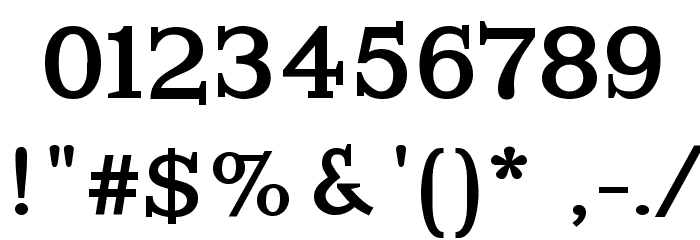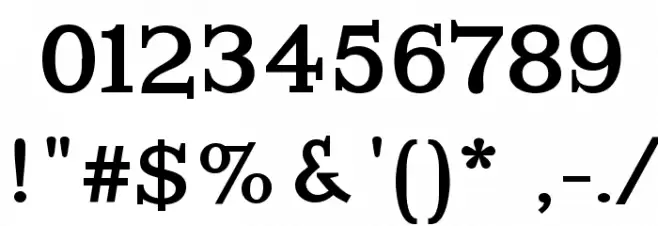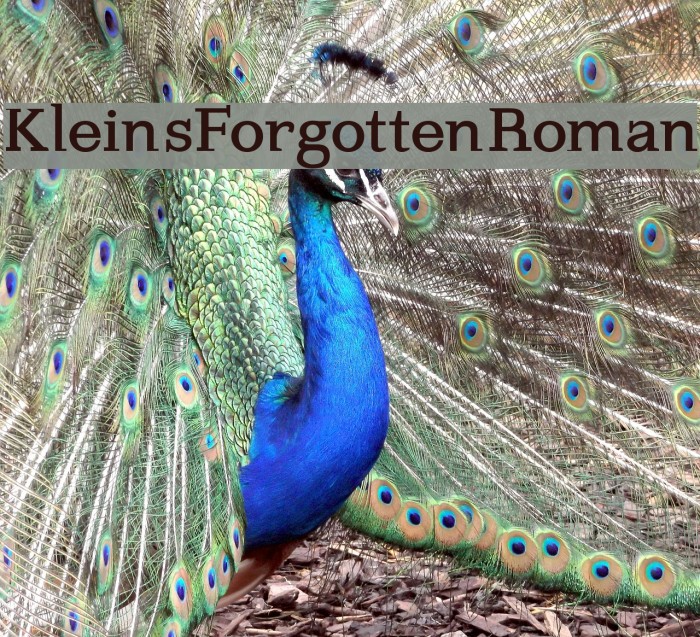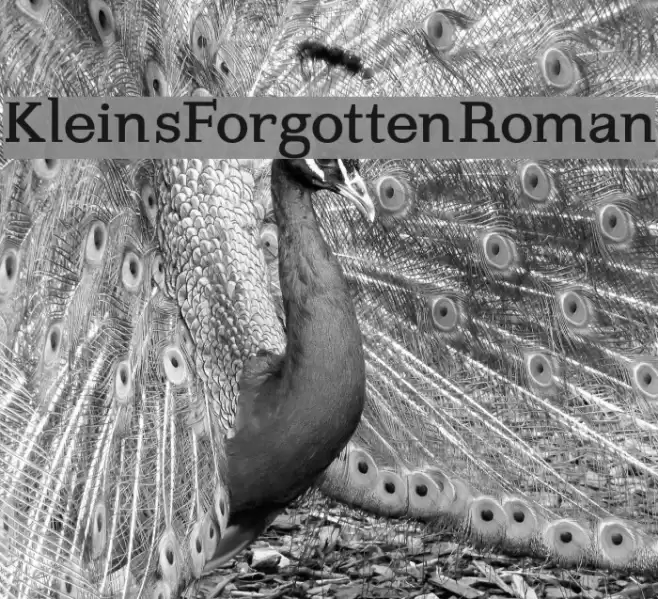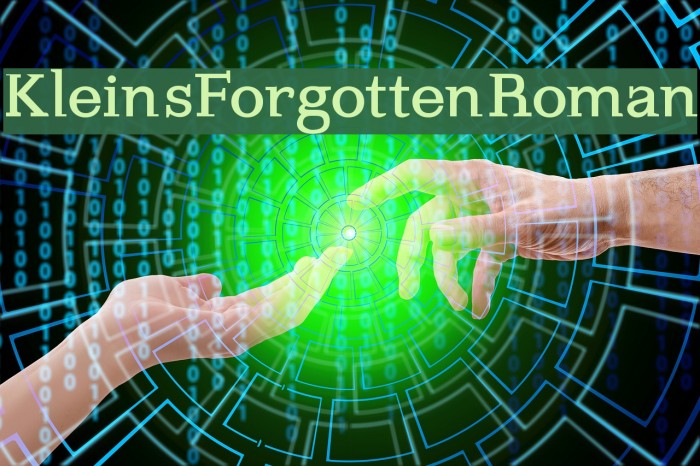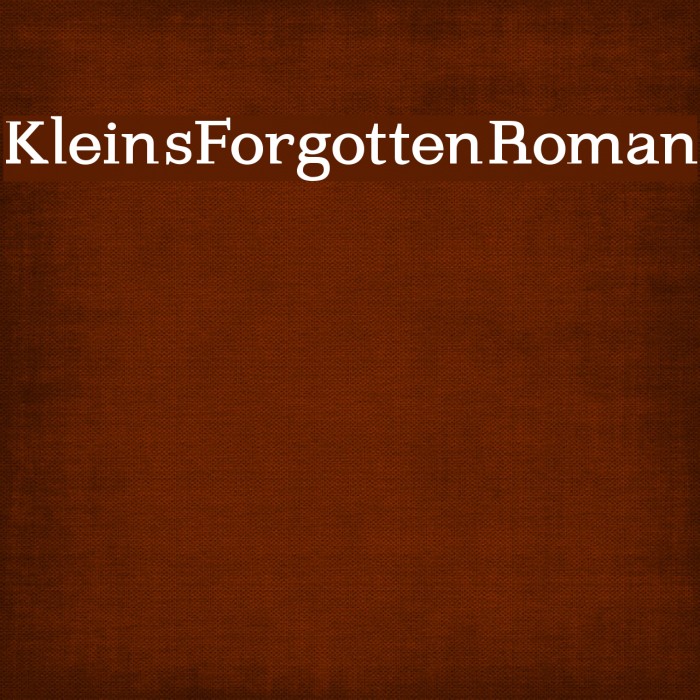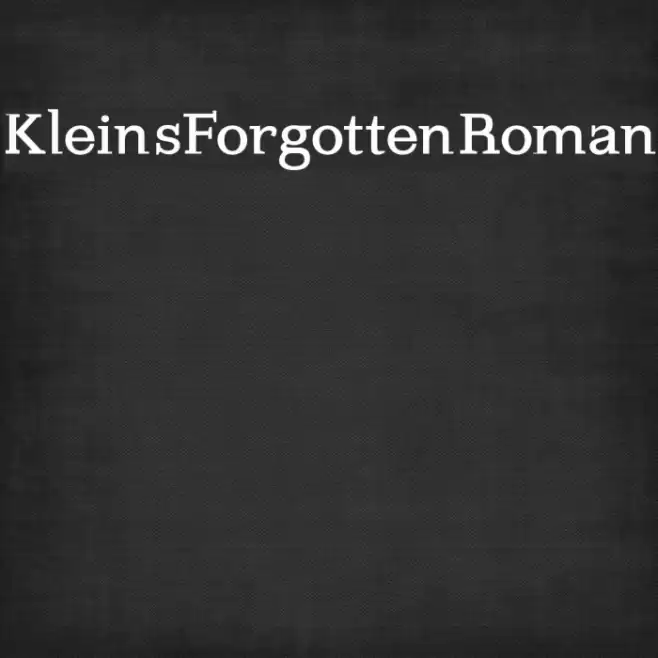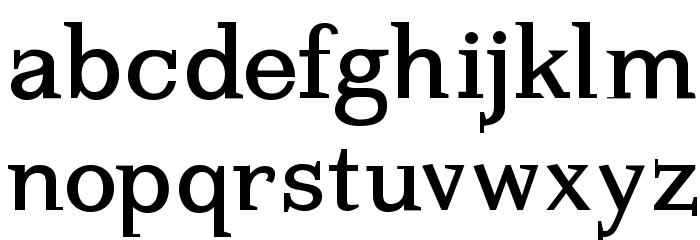
KleinsForgottenRoman Font
✎ Serif
| श्रेणियाँ | Serif |
| कंट्रास्ट | High |
| समग्र शैली | Classic |
| उपयोग का मामला | Headlines, Body text, Logos |
| सुझाए गए प्रोजेक्ट | Ideal for use in editorial design, book covers, formal invitations, and branding projects that require a touch of elegance and tradition. |